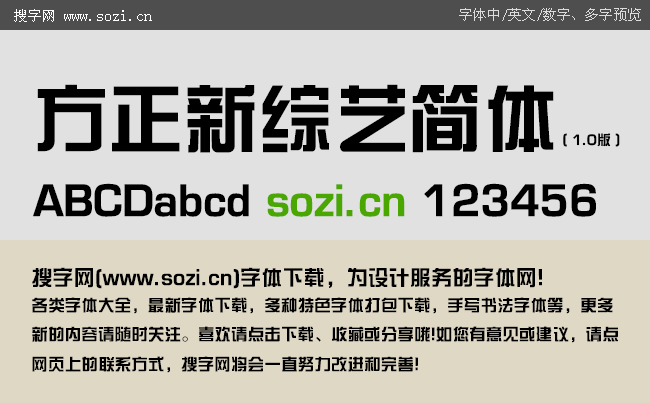
方正新綜藝簡體
搜字網(wǎng)提供一款方正新綜藝簡體字體下載。綜藝體是黑體的一種變體,也是藝術(shù)字的一種。特點是筆劃更粗,盡量將空間充滿。同時為了美觀,對拐彎處的處理較為圓潤。此款綜藝體粗細(xì)適中,適用于廣告、報刊等的標(biāo)題及海報展板等設(shè)計場合使用。
• 風(fēng)格類別: 綜藝體